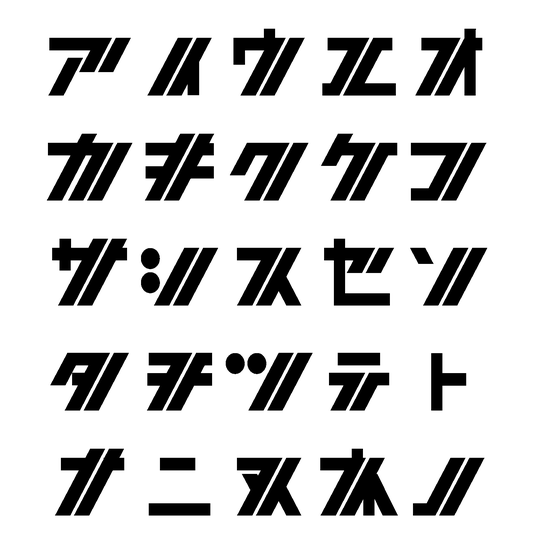
懐かしいシャープの旧ロゴを基にデザインされたフリーフォント「シャープ旧ロゴ」
シャープは1912年に創業者の早川徳次が現在の東京都江東区新大橋に金属加工業を創業したのが始まり。最初はベルトのバックルを製造しており、1915年に発明した「早川式繰出鉛筆」はいわゆるシャープペンシルで、アメリカで大ヒットし、大きく成長します。終戦後、1948年に「シャープ商事株式会社」となり、国産初の量産テレビ「TV3-14T」を生産するなど、日本を代表する総合家電メーカーとなりました。そんなシャープが過去に使っていたカタカナロゴをベースとしたフォントがシャープ旧ロゴです。
ひらがな
カタカナ
アルファベットの大文字・小文字・数字
漢字。シャープ旧ロゴ ver.2には教育漢字を中心に約2200字ほどの漢字が追加されており、漢字部分は現・パナソニックである「松下電器」を中心とする企業ロゴを基にデザインされているとのこと。なお、「シャープ旧ロゴ ver2.zip」には漢字堂電機店も同梱されているので、混植することも可能です。